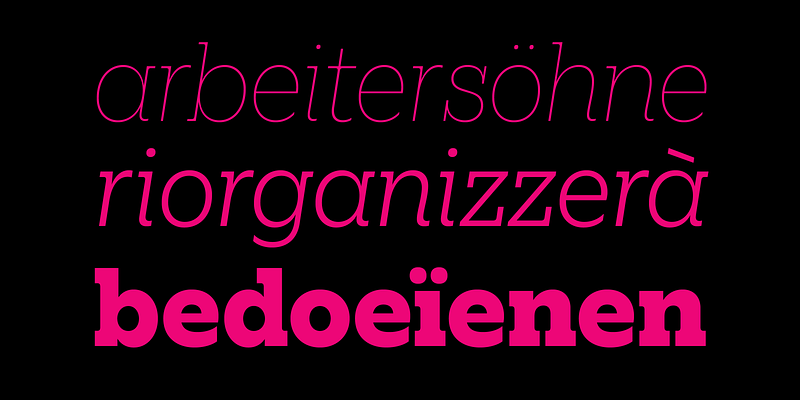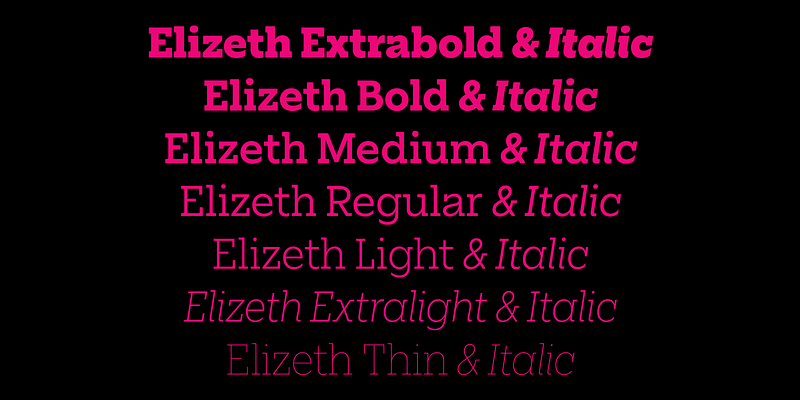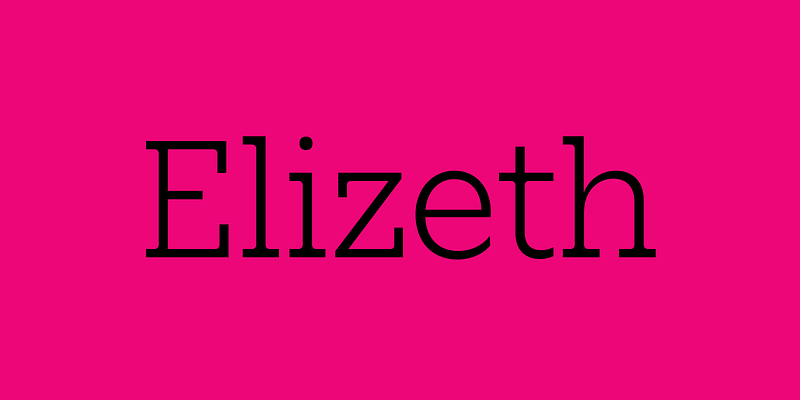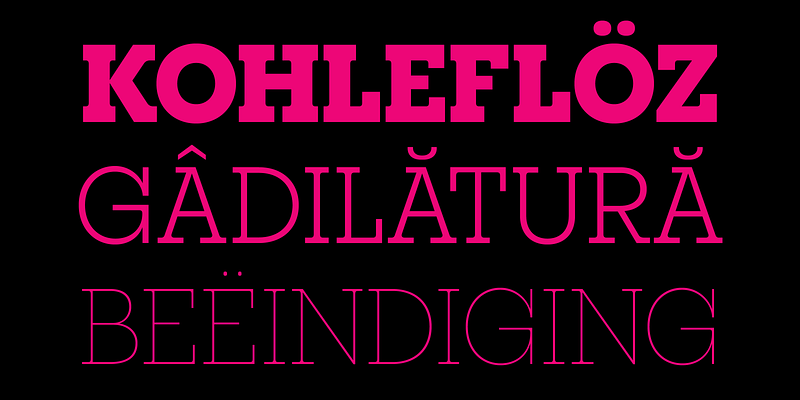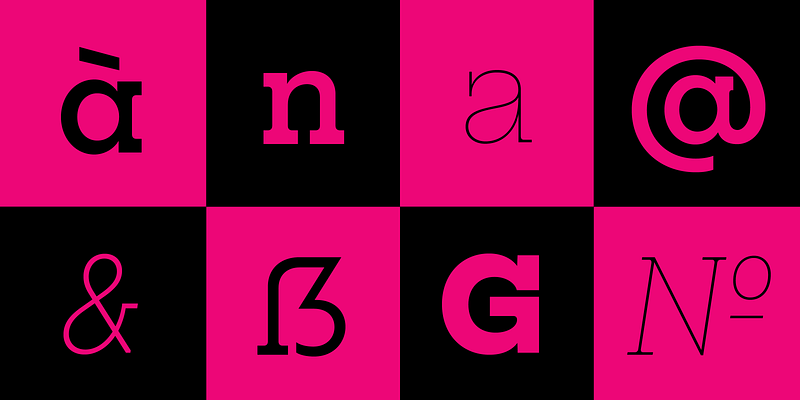
「Elizeth」は「Ofelia」のセリフ体バージョンです。2 つの幅と 7 ウエイトを持ち、様々な場面で使用できる非常に汎用性の高い書体です。標準幅は、20 世紀初頭の合理主義を想起させる、「Rockwell」などの書体と相性の良い幾何学的なスラブ体ですが、ブラケットセリフが使われています。この書体には真のイタリック体があり、幅広い言語をサポートするとともに、スモールキャピタル、オールドスタイル、タブラーなどの OpenType 機能を備えています。